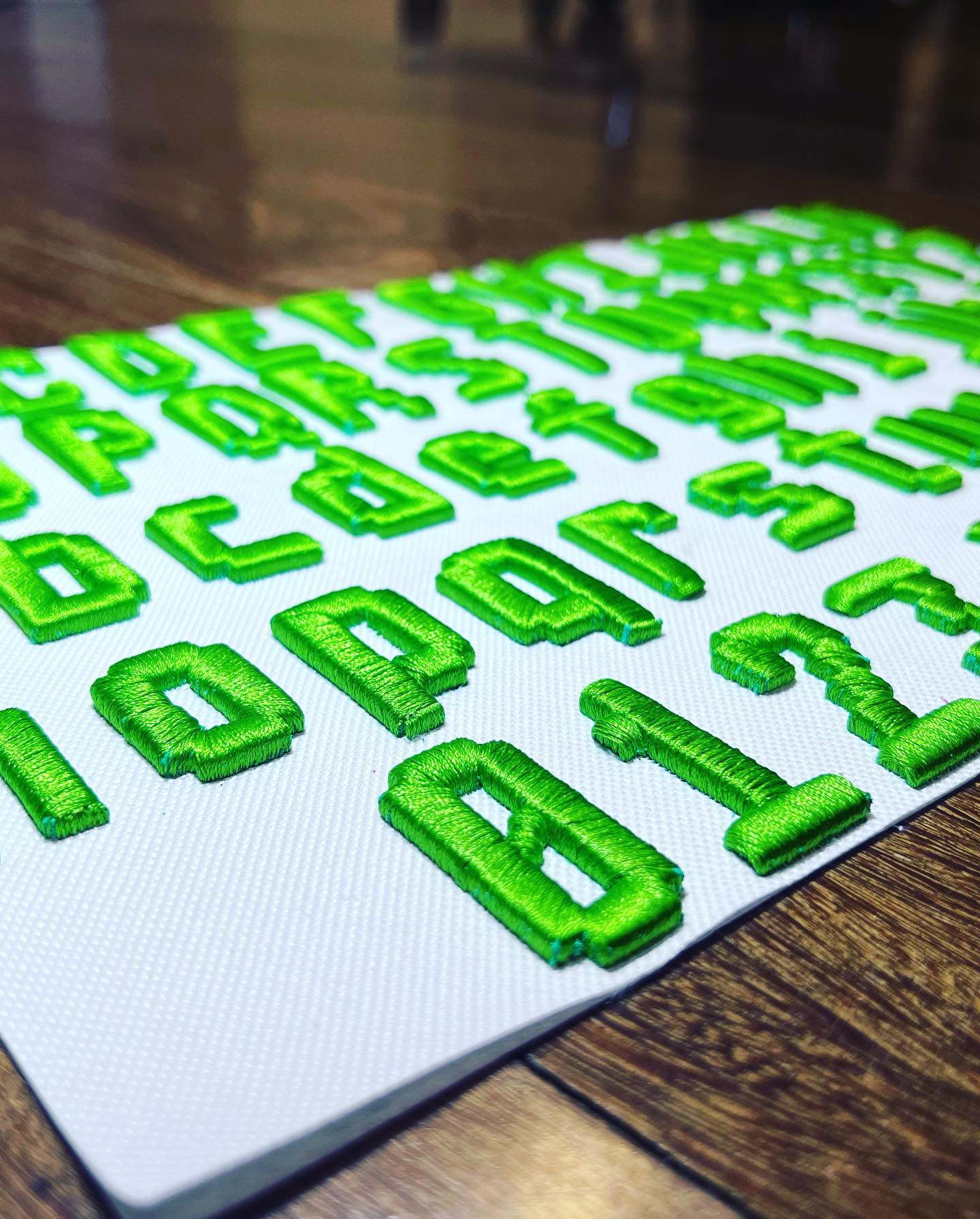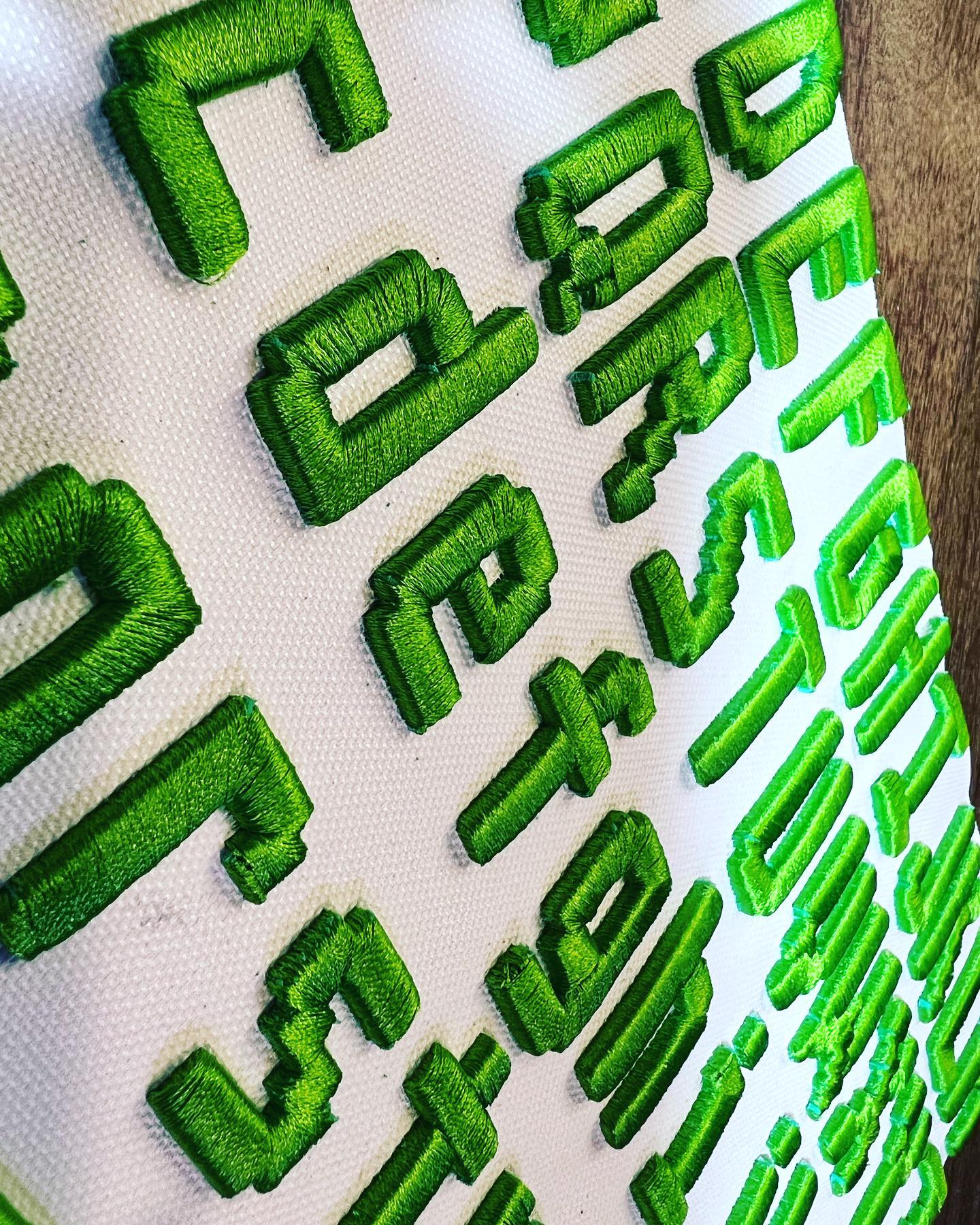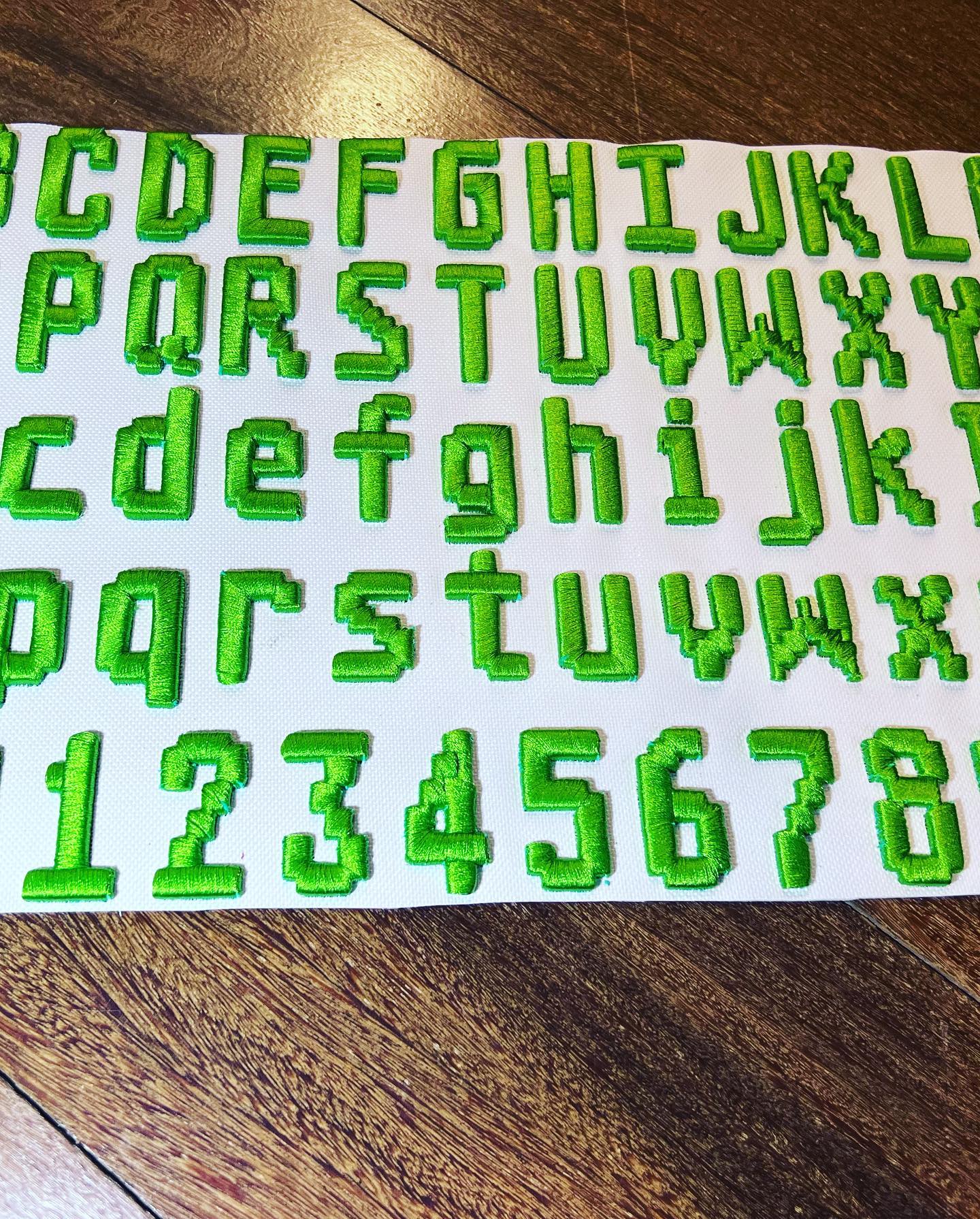
Pixel Puff Retro: مجموعة خطوط التطريز ثلاثية الأبعاد المستوحاة من Atari
استمتع بالعصر الذهبي للألعاب مع PixelPuff Retro ، مجموعة خطوط تطريز جريئة تعيد إحياء الخطوط الأيقونية جماليات أتاري 8 بت في مجد نفخة ثلاثية الأبعاد اللمسية.
تم تصميم كل حرف كبير وصغير ورقم لمحاكاة الكمال البكسل القديم، مع رفع مستوى الخياطة الرغوية المرفوعة للحصول على أجواء ثلاثية الأبعاد وجاهزة للعب في الممرات.
من اللون الأصفر الخاص بـ Pac-Man إلى اللون الأخضر الخاص بـ Space Invader، يمكنك تخصيص تصميماتك بألوان خيوط نابضة بالحياة تتناسب مع القبعات.
أصالة 8 بت: شخصيات مجسمة، بكسل مثالية تصرخ الحنين إلى ألعاب الأركيد في الثمانينيات .
نسيج الأركيد ثلاثي الأبعاد: تضيف الطبقة السفلية من الرغوة عمقًا، وتحول البكسلات المسطحة إلى فن ملموس يستحق عصا التحكم.
مجموعة الشخصيات الكاملة: اصنع شعارات أو علامات لاعبين أو عبارات محفظة العملات المشفرة باستخدام الاتساق AZ وaz و0-9.
مثالية لفرق الرياضات الإلكترونية، أو البضائع القديمة، أو أزياء المهوسين بالتكنولوجيا، بيكسل باف ريترو يُدمج أسلوب المدرسة القديمة الرائع مع لمسة أزياء الشارع الحديثة. إنتهت اللعبة؟ أبدا.